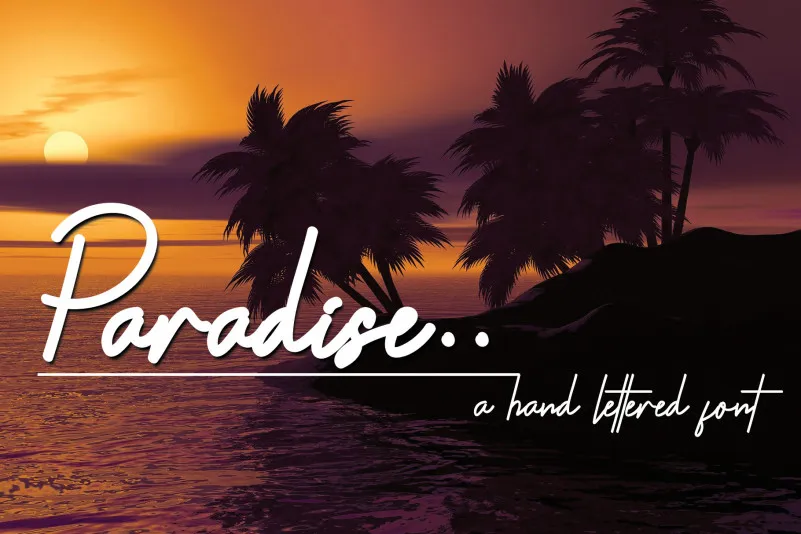
Paradise Font
Descrição para Paradise Font: Paradise é uma fonte escrita à mão relaxada que oferece uma experiência visual agradável e fluida. Ela se destaca por sua naturalidade, permitindo-lhe expressar seu criativismo de maneira autêntica. Adicionar Paradise ao seu próximo projeto transformará seus ideias em algo único e marcante. Seja para um design de marca ou até mesmo uma mensagem pessoal, Paradise garante que seus escritos destacem-se da multidão. Esta fonte foi projetada pelo Erik Studio, conhecido por suas habilidades criativas na área das fuentes. Com sua caligrafia espontânea e vibrante, Paradise é perfeita para aqueles que buscam um toque de personalidade em seus designs digitais. Ela se adapta facilmente a diversos formatos gráficos e pode ser usada tanto no design de logotipos quanto em texturas e tipografia customizadas. Com Paradise na sua coleção, você terá à mão uma fonte que não apenas complementará seu trabalho, mas o fará destacar-se em um mundo digital cada vez mais cheio de recursos visuais. Que tal experimentar Paradise hoje? Sua criatividade pode se beneficiar muito dessa fonte relaxada e autêntica!